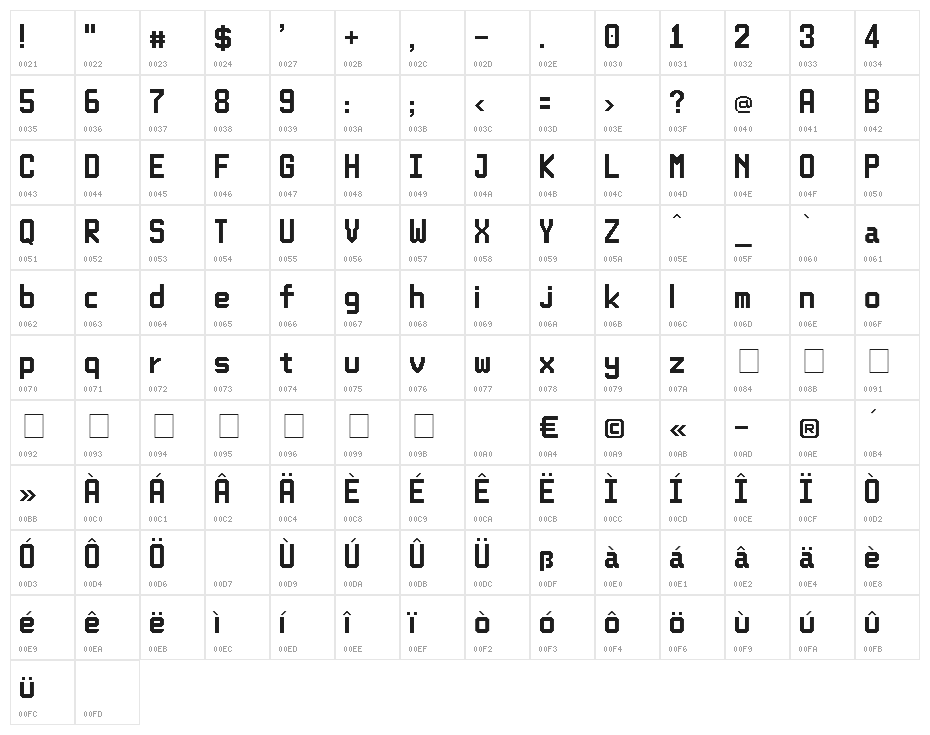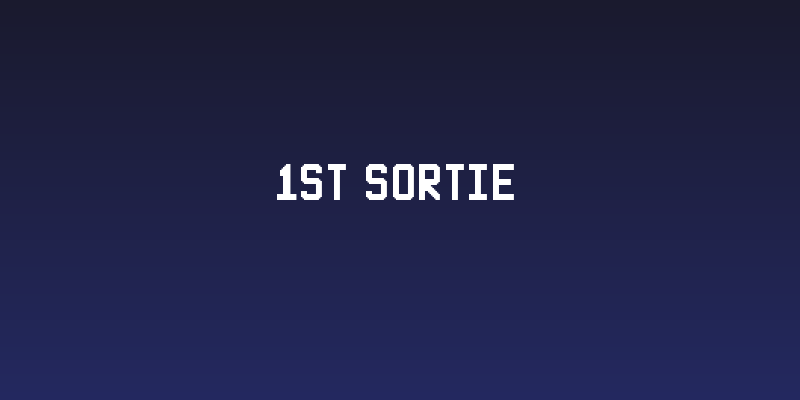
1st Sortie Font
| 整体风格 | Retro, Digital |
| 推荐项目 | Ideal for video game design, tech-themed posters, retro digital art, and any project seeking a nostalgic or digital look. |